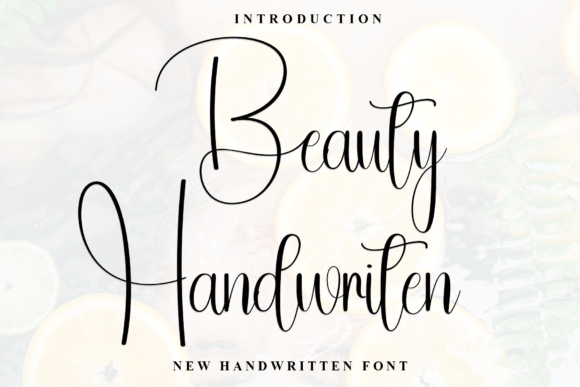
Beauty Handwriten
قد يكون العثور على عناصر التصميم المناسبة أمرًا صعبًا، ولكن Beauty Handwriten يقدم مجموعة استثنائية ترتقي بعملك على الفور.
سواء كنت تقوم بإنشاء منتجات الطباعة عند الطلب أو دعوات الزفاف أو رسومات وسائل التواصل الاجتماعي، فإن Beauty Handwriten هو الخيار المثالي.